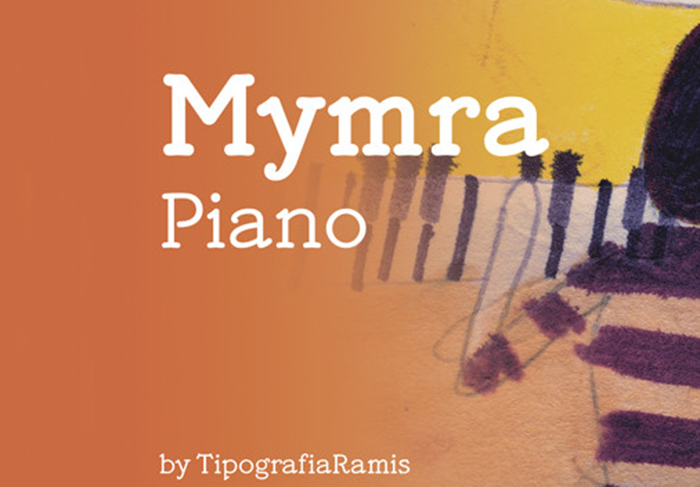
Introduzimos Mymra Piano! Esta é uma fonte premium vendida na MyFonts, mas hoje está disponível gratuitamente para download. Mymra Piano é uma face serif romana monoline que se inspira no traçado de Charles Robinson do período Art Nouveau. Esta elegante fonte serif oferece um toque sofisticado e refinado aos seus projetos, com linhas sólidas e finas que refletem a arte da letra do período Art Nouveau. Inspirada na influência de Charles Robinson, Mymra Piano traz uma atmosfera nostálgica e elegante para qualquer projeto que você esteja desenvolvendo. Seja em um design de cartão de visita, um layout jornalístico ou até mesmo no design gráfico da web, a Mymra Piano dará um toque diferenciado aos seus designs. Ela é perfeita tanto para o seu trabalho profissional quanto para projetos criativos pessoais que valorizam uma pitada de arte e elegância. Descubra por si mesmo como esta fonte serif proporcionará uma experiência única a seus designes, fazendo do Mymra Piano um complemento indispensável no seu leque de ferramentas gráficas.